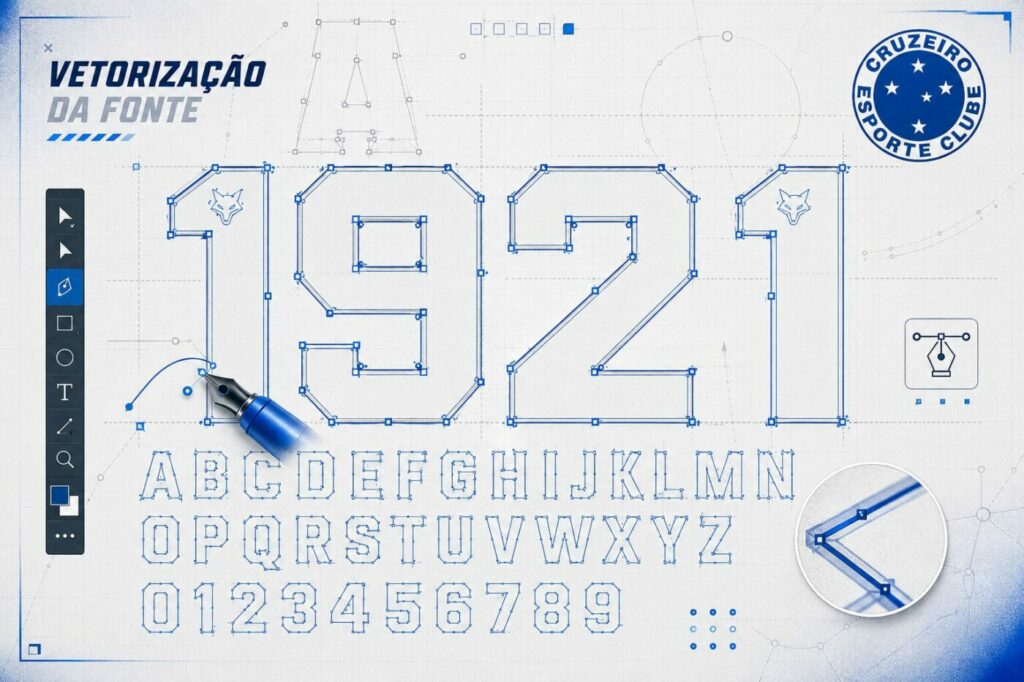
Se você é designer, trabalha com sublimação ou é um torcedor apaixonado criando artes para as redes sociais, contar com a fonte do Cruzeiro 2026 com precisão e alta qualidade faz toda a diferença no resultado final do projeto.
Para a temporada 2026, a tipografia do time traz uma estética marcante, com traços retos, cantos chanfrados e um detalhe exclusivo que remete à identidade do clube.
Características da Tipografia da Camisa do Cruzeiro 2026
A coleção de uniformes do Cruzeiro para a temporada destaca-se pelo equilíbrio entre modernidade e tradição. A tipografia utilizada nas costas do manto acompanha essa linguagem visual:
- Estilo Robusto e Geométrico: As letras e os números possuem um formato condensado e reto, garantindo excelente leitura à distância tanto no estádio quanto nas transmissões de TV.
- Cantos Chanfrados: Diferente de fontes totalmente arredondadas ou pontiagudas, os números contam com cortes angulares nos cantos, conferindo um visual esportivo e dinâmico.
- Símbolo da Raposa nos Números: O grande diferencial da temporada 2026 é a inclusão da silhueta do mascote (a Raposa) no topo de cada número, posicionada no centro superior de dígitos como o 0, 1, 2, 3, 4, 5, 6, 7, 8 e 9.
- Linhas Contornadas: Os números trazem uma moldura/contorno fino que destaca o preenchimento interno, facilitando a aplicação em fundos escuros (como a camisa titular azul) ou claros (como a camisa reserva branca).
- Alfabeto Completo com Acentuação: O vetor inclui caracteres especiais (como Á, Ç, É, Ô, Ü, Ñ), permitindo a personalização de qualquer nome sem adaptações improvisadas.